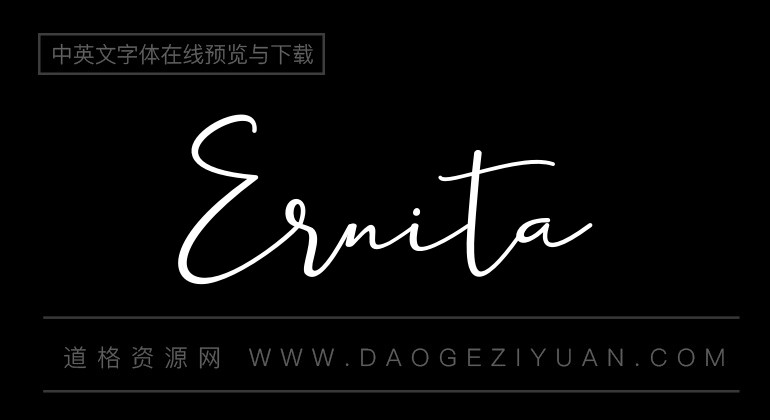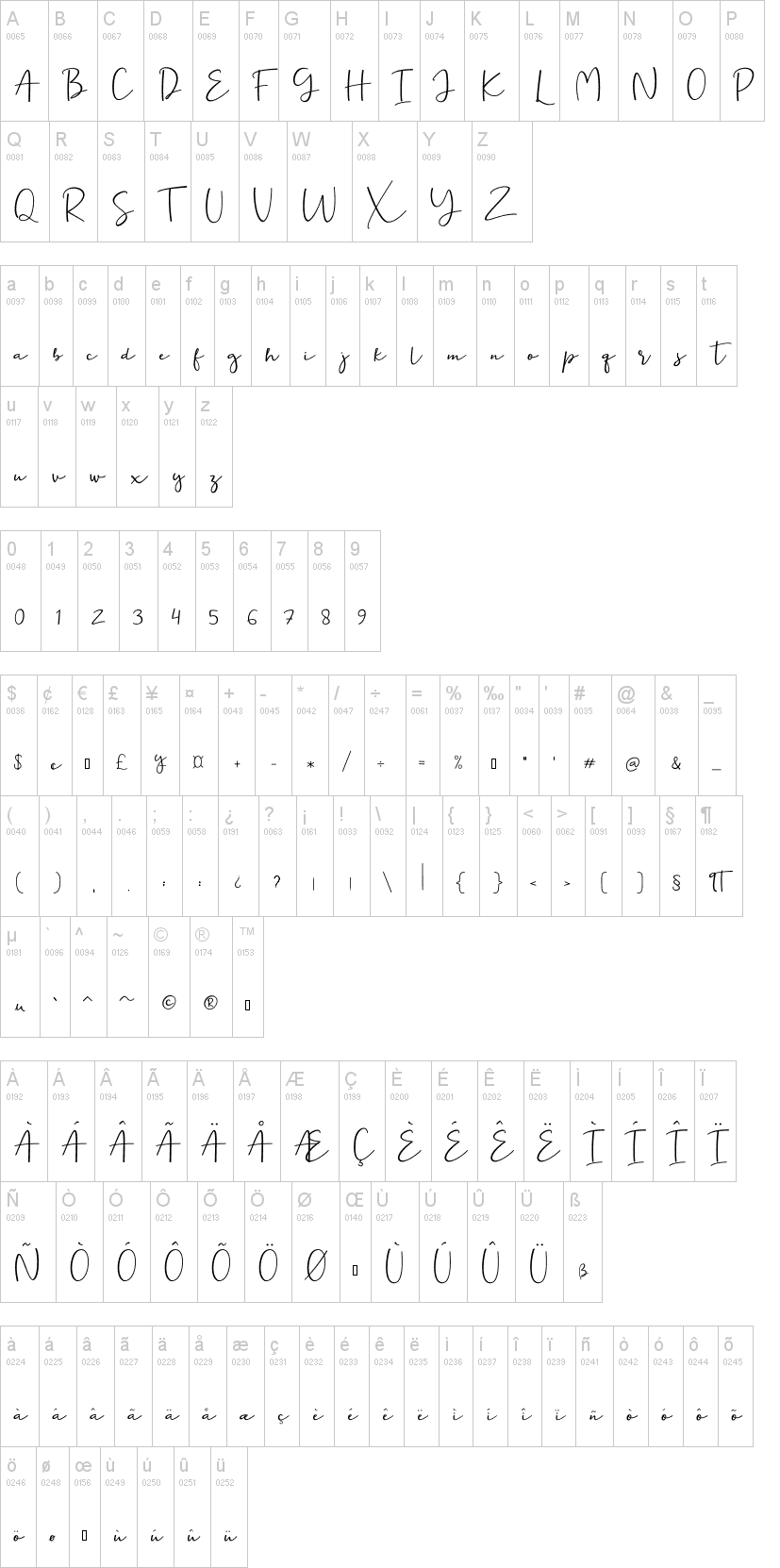
Ernita 字体是一款由西班牙设计师 Ermano D'Orazio 为英文、西班牙文和其他拉丁文字体设计的字体。它的特点是细节丰富,曲线优美,字形稳定,并具有良好的可读性。Ernita 字体适用于海报、书籍、网页和其他文字应用场景,可以让文字具有更强的表达力。内容介绍
Ernita是一款非常不错的手写艺术字体,具有很好的视觉感,适合于文化类的宣传设计、商业类品牌的广告和产品包装设计以及个性化文字排版等较多场景。